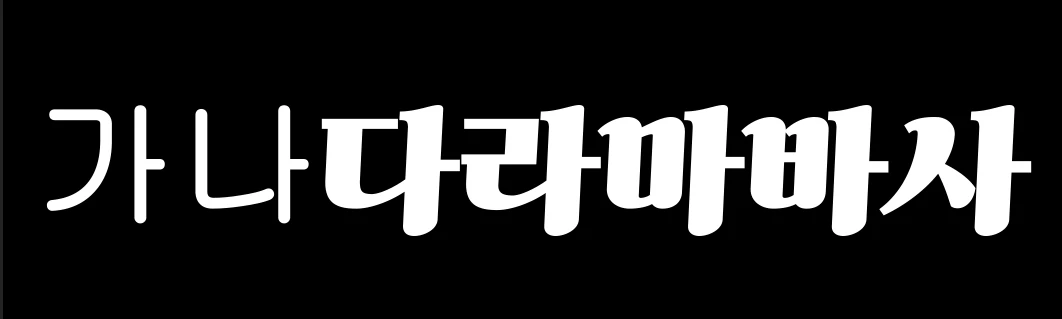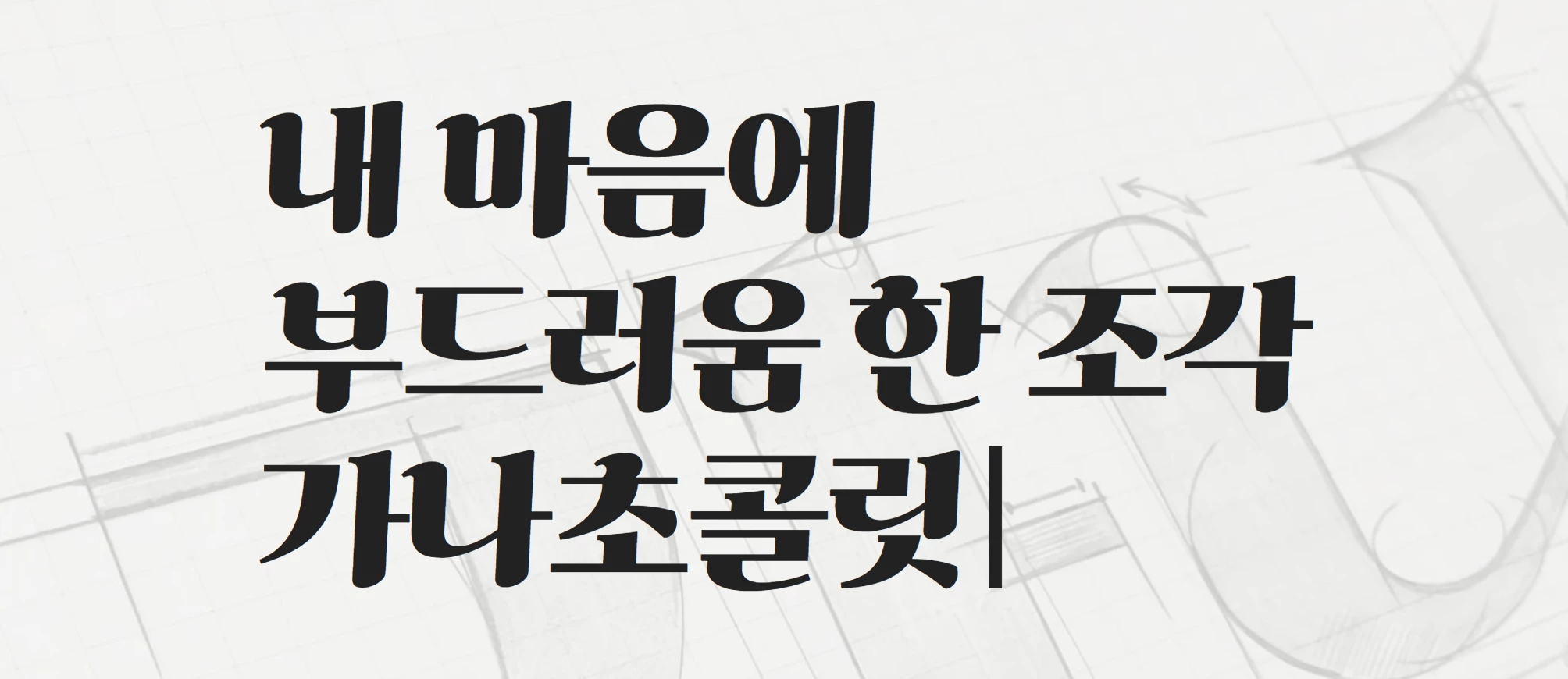
After effects 한글 폰트가 일러스트랑 다르게 더 굵게 나오는 오류 현상
after effects 폰트 풀려서 굴림체로 나오는 오류도 문제지만
기존 폰트보다 에펙에 적용한 폰트가 stroke가 더 붙은 것처럼 굵게 나오는 오류가 있는 것 같습니다.
예시로 올린 검은 배경 이미지는 에펙에서 적용한 것이고
하얀 배경 이미지는 일러스트에서 적용한 것입니다.
폰트명은 가나초콜릿 폰트 입니다.
아시다시피 가로선이 가는편인데 에펙에 적용하니 스트로크 추가된 것처럼 두꺼워집니다.
다른 폰트도 두껍게 적용되고 있고 어도비 폰트또한 같은 오류가 나는 거 같습니다.
레이어에 따로 스트로크 적용된 것 없고요. PC 재부팅도 해보고 24버전 25버전에서 테스트했는데 동일합니다. 이부분 해결 방법 있나요?